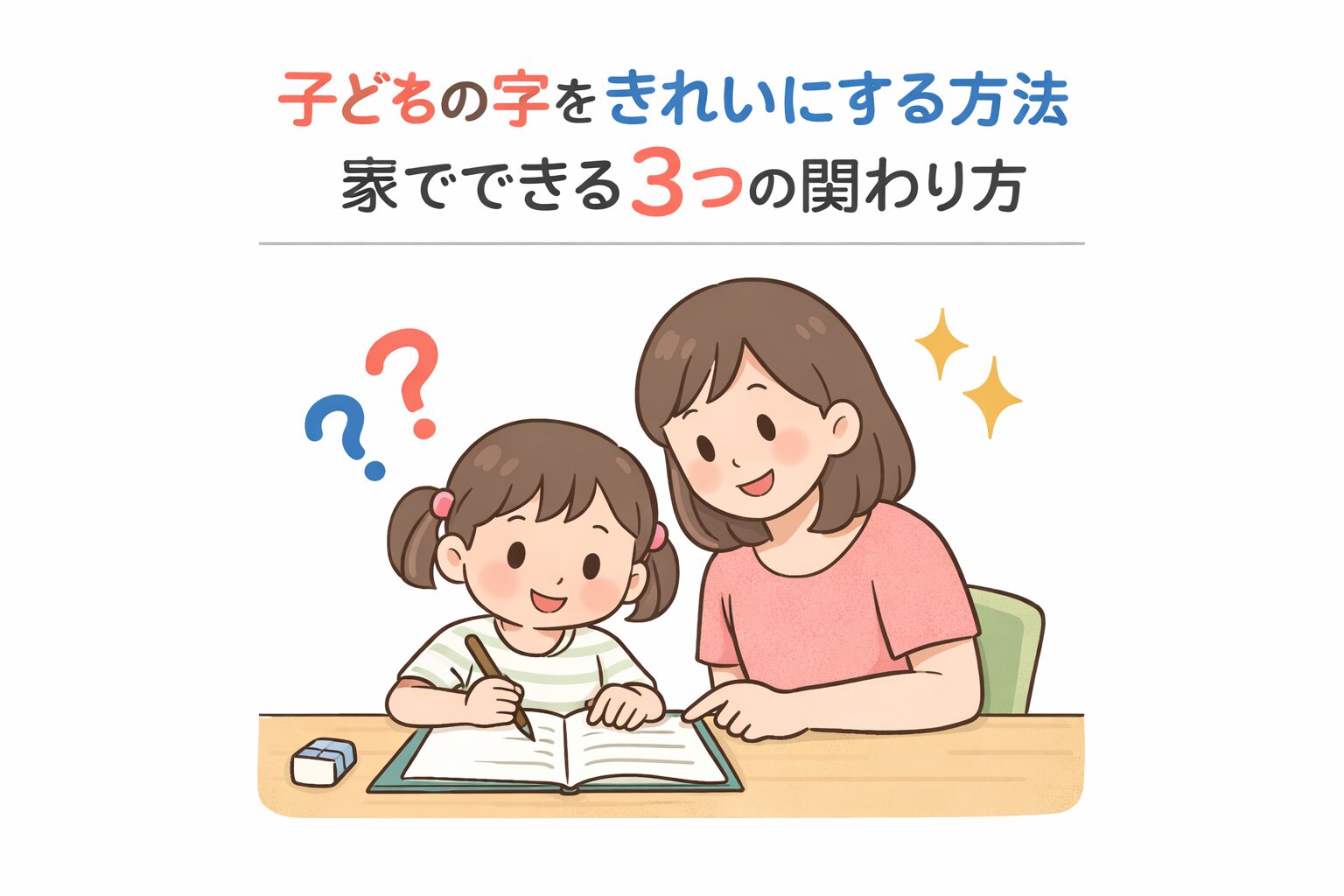
子どもの字をきれいにする方法|家でできる3つのこと
「子どもの字が下手なんだけど、どうすればいいの?」
「宿題見てると、字がひどくて…」
そんな話を、親御さん同士がしているのを
よく耳にします。
子どもの字が気になっても、
どう関わればいいのかは意外と難しいものですよね。
子どもの字をきれいにする方法として、よく言われるのは
・姿勢を良くする
・鉛筆の持ち方を直す
・「ゆっくり丁寧に、ゆっくり丁寧に…」と言い続ける
といったことです。
もちろん、どれも大切なことです。
でも実際には、それだけで
子どもの字が大きく変わることはあまり多くありません。
今日はそうした一般的な話ではなく、
私が教室で子どもたちを見ていて効果を感じている関わり方を
3つご紹介します。
特別な道具や練習は必要ありません。
家で字を見てあげるときの、ほんの少しの関わり方です。
① いい字を見つけて伝える
まず一つ目は、
上手に書けているところを見つけて伝えること
です。
もし字の中で一文字見つけるのが難しかったら、
・まっすぐ線が引けている
・はらいがきれいに書けている
そんな小さなところでも大丈夫です。
例えば
「この字、とても読みやすいね」
「この線、とてもよく書けてる!」
そんなふうに伝えてみてください。
このときに大事なのは、
「この字はきれいじゃないね」
「これは惜しいね」
といった言葉は言わないことです。
良くないところを探すのではなく、
いいところを見つけることに専念する。
そして、見てあげるたびに
一つだけ見つけて伝える。
それだけで十分です。
② 子どもに「どうやって書いたの?」と聞く
上手に書けた字を見つけたら、
こんなふうに聞いてみてください。
「どうしたらそうやって書けたの?」
「何か秘訣があるの?」
もし
「ない」
と言われたら、
「そっか〜」
で終わりで大丈夫です。
もし何か教えてくれたら、
「そうなんだ、いいこと聞いた!」
と受け取ります。
ここで大事なのは、
親は聞き役に徹することです。
親の考えを説明したり、
書き方を教えたりする必要はありません。
子どもが自分の書き方を言葉にすることで、
少しずつ意識が変わっていきます。
③ 字が変わる前に、字との向き合い方が変わります
この関わり方を続けていると、
すぐに字が劇的に変わるわけではありません。
でも、子どもの
字を書くときの向き合い方
が少しずつ変わっていきます。
急いで書くのではなく、
「丁寧に書こう」
という気持ちが生まれてくるのです。
実は多くの親御さんは、
「すごく上手な字を書いてほしい」
というより
「丁寧に書いてほしい」
と思っているのではないでしょうか。
この関わり方を続けていると、
子どもは少しずつ
丁寧に書く字
が増えていきます。
丁寧に書くためのポイント
字を丁寧に書くときには、
・折れる
・とめる
・止めてから払う
・はねる
・まっすぐの線を書く
こういったことを意識すると
自然と字が整っていきます。
なぜなら、これらは
時間がかかる動き
だからです。
つまり、これができているときは
子どもが
丁寧に書こうとしている証拠
でもあります。
そんな字を見つけたら、
「ここ、とてもよく書けてるね」
と伝えてあげてください。
過剰に褒める必要はありません。
ただ、
気づいて伝えてあげること
それだけで十分です。
小さな「できている」が、次の一歩になります
子どもの字が気になると、
「もっと丁寧に書きなさい」
と言いたくなることもありますよね。
でも、子どもにとっては
「どうすればいいのか分からない」
ことも多いものです。
だからこそ、
・いいところを見つける
・どうやって書いたのか聞く
そんな小さな関わりが、
字を書く気持ちを少し変えていくことがあります。
もしお子さんの字が気になっているなら、
まずは一度、字を一緒に見てみてください。
小さな「できている」を見つけることが、
次の一歩につながることもあります。